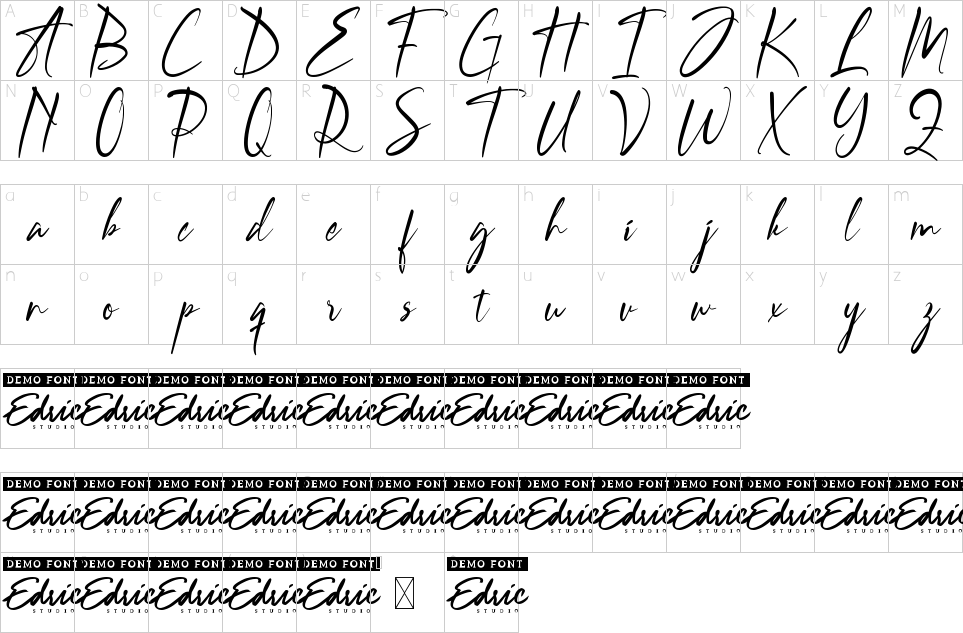
A fonte Sagittary é uma grata surpresa para os designers gráficos e webmasters que procuram uma opção gratuita e versátil. Desenvolvida pelo designer desconhecido EdricStudio, Sagittary é uma fonte de corpo médio que oferece uma combinação harmônica de facilidade de uso e estilo. Com seu design elegante, Sagittary é perfeito para aplicativos como ações e menus, e também se destaca como uma fonte de estilo para textos de corpo e subtítulos. Como uma fonte gratuita de alta qualidade, Sagittary já foi baixada 3.215 vezes, evidenciando seu valor e popularidade. Se procura uma fonte moderna e funcional que não comprometa sua criatividade, a Sagittary pode ser o seu próximo favorito.